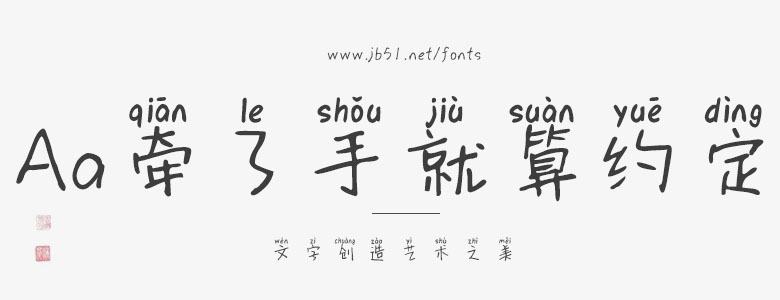
Aa牽了手就算約定是一款賞心悅目的藝術(shù)字體,該字體筆觸較為粗實(shí),字體清晰,具有很好的視覺效果,適合應(yīng)用于藝術(shù)設(shè)計(jì)、平面宣傳設(shè)計(jì)、網(wǎng)頁(yè)設(shè)計(jì),書法字貼等領(lǐng)域。需要的朋友不妨前來本站下載使用。